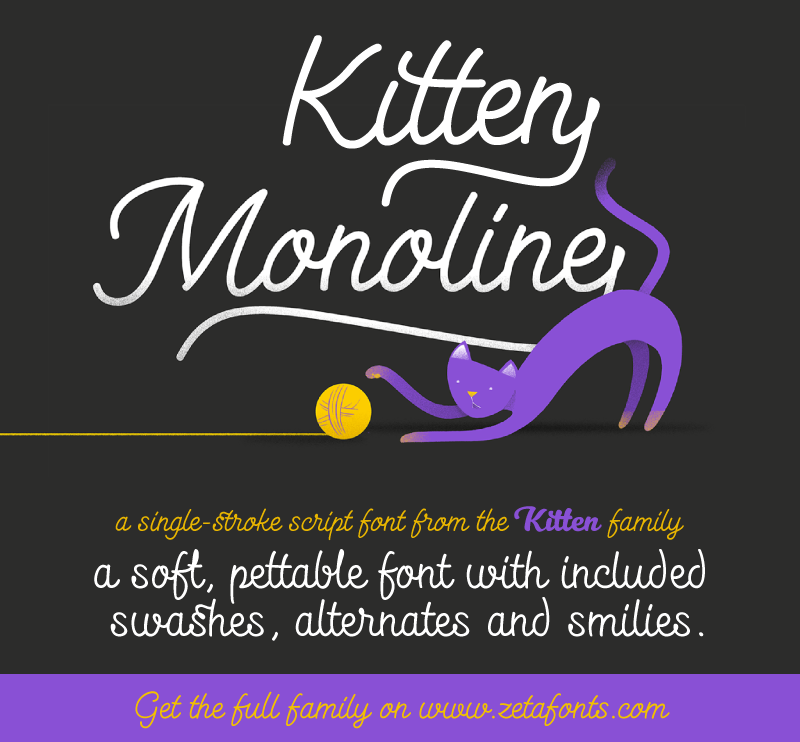
A Kitten Monoline é a versão single-stroke do famoso conjunto de scripts Kitten, criado por Cosimo Lorenzo Pancini. Este conjunto, com múltiplas pesos e uma aparência que evoca os desenhos de um sign-painter, oferece uma ampla gama de variante, alternativas e ligações. O design leva em conta a estética caters do mundo real e tem uma personalidade única e divertida, ideal para se conectar com as crianças ou criar gráficos infantis. Além disso, Hamilton adicionou “cat dingbats” às figuras extras deste conjunto de fontes, tornando-a ainda mais interessante e atraente. Esta fonte é uma excelente opção para quem busca algo divertido e criativo para adicionar um toque único ao seu design gráfico ou material de marketing.